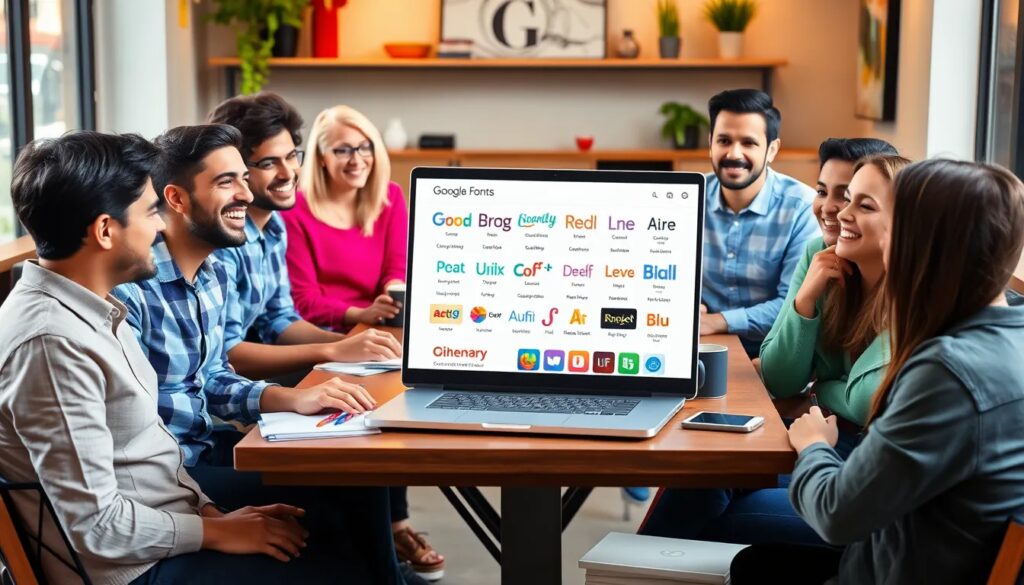
Free font google: la mejor selección de tipografías gratis
Si estás buscando fuentes gratis en Google Fonts, has llegado al lugar indicado. Google Fonts ofrece una impresionante selección de tipografías que son perfectas para cualquier proyecto, ya sea personal o profesional. A continuación, exploraremos todo lo que necesitas saber sobre estas fuentes y cómo puedes utilizarlas.
Desde su lanzamiento, Google Fonts ha revolucionado la manera en que los diseñadores y desarrolladores acceden a tipografías de alta calidad. Con más de 600 opciones disponibles, la variedad y calidad son simplemente inigualables.
¿Qué es Google Fonts?
Google Fonts es un servicio de Google que permite a los usuarios acceder a una amplia biblioteca de tipografías gratis. Estas fuentes están diseñadas para ser utilizadas tanto en proyectos web como en aplicaciones de escritorio. La plataforma ofrece más de 900 familias de fuentes, todas de código abierto.
La principal ventaja de Google Fonts es su facilidad de uso. Puedes integrar estas fuentes en tu sitio web o descargar archivos para utilizarlos en programas de diseño gráfico sin complicaciones. Además, las fuentes están optimizadas para la web, lo cual garantiza una carga rápida y un rendimiento óptimo.
Con Google Fonts, no solo obtienes acceso a fuentes de calidad, sino que también puedes contribuir al ecosistema de diseño, ya que muchas de estas tipografías son creadas por diseñadores independientes y estudios de diseño.
¿Para qué sirve Google Fonts?
La utilidad de Google Fonts es múltiple. Principalmente, sirve para mejorar la estética de un sitio web o un proyecto gráfico. A continuación, te enumeramos algunas de sus funciones más destacadas:
• Estilizar tu contenido: Las tipografías pueden cambiar completamente la percepción de un texto.
• Mejorar la legibilidad: Algunas fuentes están diseñadas específicamente para ser más legibles en pantallas.
• Incluir variedad: Con más de 600 opciones, puedes encontrar combinaciones únicas que se adapten a tu proyecto.
• Usar en múltiples plataformas: Las fuentes son aptas para WordPress, Photoshop y otras aplicaciones de diseño.
En resumen, Google Fonts es una herramienta esencial para cualquier diseñador que busque fuentes gratuitas que se integren fácilmente en sus proyectos.
Las 15 tipografías de Google Fonts más populares
A continuación, exploramos algunas de las mejores fuentes para diseño web en Google Fonts, que han ganado popularidad entre diseñadores y desarrolladores:
• Montserrat: Ideal para encabezados y textos destacados, esta fuente sans serif es moderna y versátil.
• Open Sans: Conocida por su legibilidad, es perfecta para textos largos y web.
• Poppins: Su diseño geométrico la hace atractiva para proyectos creativos.
• Roboto: Una fuente sans serif que combina lo clásico y lo moderno, ideal para interfaces.
• Lora: Perfecta para proyectos editoriales, se adapta bien a textos de cuerpo.
Además de estas, hay muchas otras fuentes disponibles que se adaptan a diferentes estilos y proyectos. Puedes explorar la biblioteca completa para encontrar la que mejor se ajuste a tus necesidades.
¿Cómo utilizar Google Fonts en tu web?
Incorporar Google Fonts en tu sitio web es un proceso muy sencillo. Aquí te explicamos cómo hacerlo:
1. Selecciona las fuentes: Accede a Google Fonts y elige las tipografías que deseas utilizar.
2. Integra el enlace: Copia el enlace proporcionado por Google y pégalo en la sección <head> de tu HTML:
4. Usa la fuente en CSS: Aplica la fuente en tus estilos CSS usando la propiedad font-family.
Este método permite que las fuentes se carguen automáticamente cuando alguien accede a tu sitio, lo cual mejora la experiencia del usuario y el diseño general.
Consejos a tener en cuenta a la hora de elegir tu tipografía en Google Fonts
Elegir la tipografía adecuada puede ser determinante para el éxito de tu proyecto. Aquí hay algunos consejos que te pueden ayudar:
• Define el propósito: Considera el mensaje que deseas transmitir y el público al que te diriges.
• Combina fuentes: No dudes en mezclar diferentes tipos de fuentes para crear contraste y dinamismo. Por ejemplo, combina una fuente serif para los encabezados con una sans serif para el cuerpo del texto.
• Prueba la legibilidad: Asegúrate de que la fuente sea legible en diferentes tamaños y dispositivos.
• Considera el entorno: Piensa en cómo se verá tu texto en pantalla o impreso, dependiendo del medio que estés utilizando.
Recuerda que la elección de la tipografía debe alinearse con la identidad visual de tu marca y el mensaje que deseas comunicar.
Con esta guía, ahora tienes toda la información necesaria para explorar el mundo de las fuentes gratis en Google Fonts. Desde su descarga hasta consejos para su uso, estás listo para comenzar a diseñar con estilo.